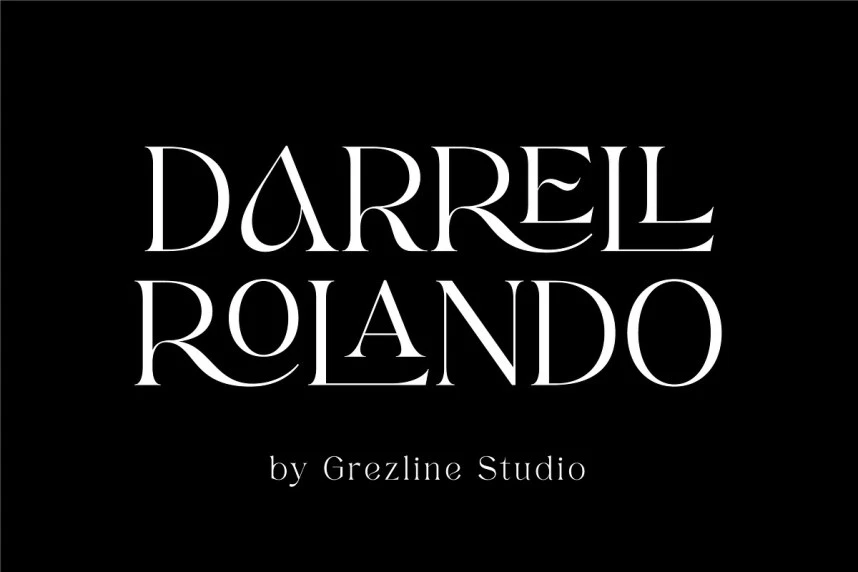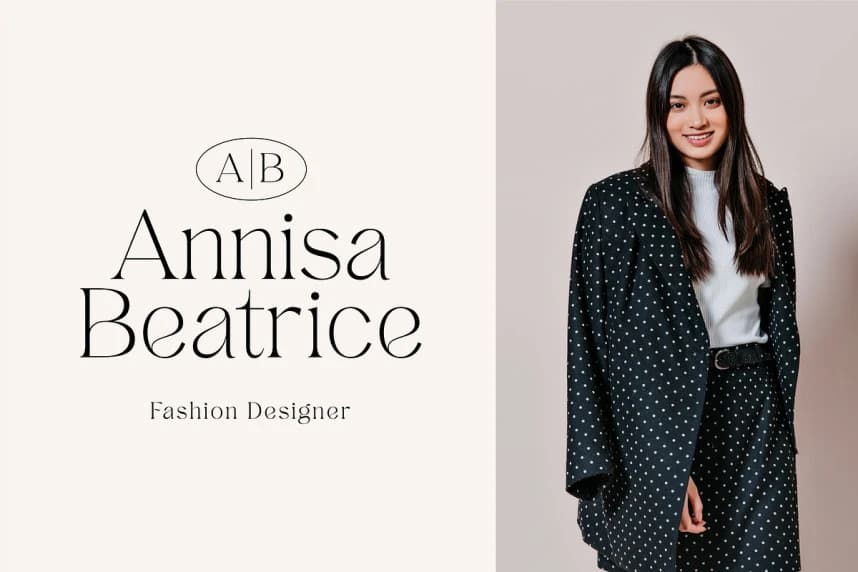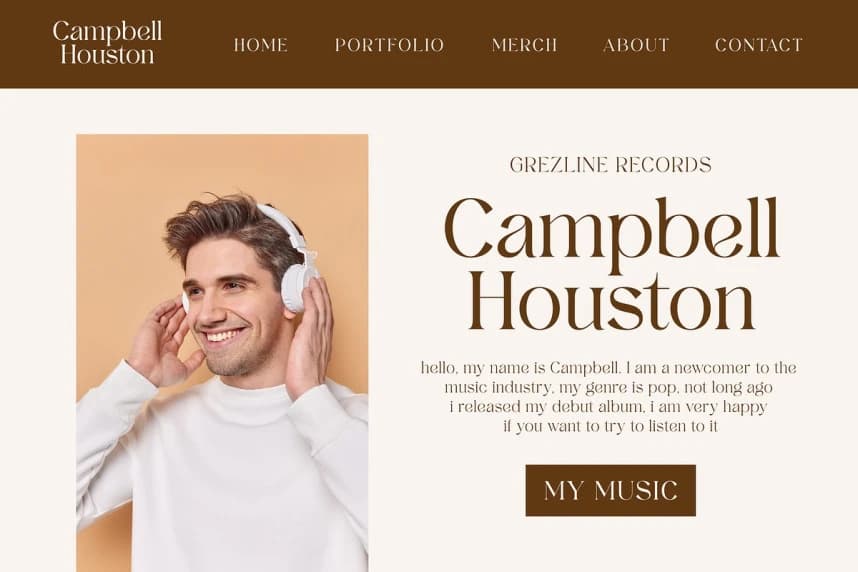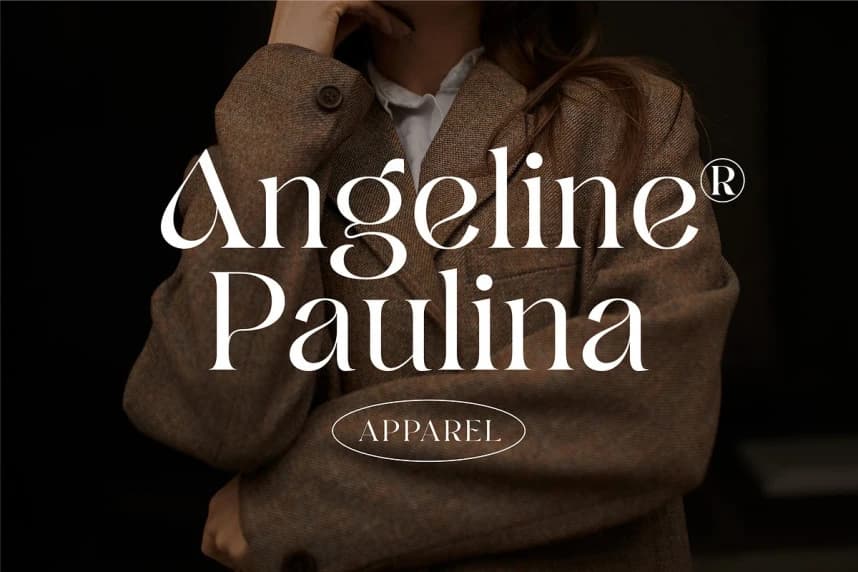
Darrell Rolando Font, vintage ve klasik görünümlere sahip şık bir başlık yazı tipidir. Bu yazı tipi, benzersiz bir ligatür karakter seti ile birlikte gelir. Logo, başlıklar, unvanlar, davetiyeler, etiketler, dergiler, kitaplar, tebrik ve düğün kartları, ambalaj, moda ve makyaj için çok uygundur.
Darrell Rolando Font, vintage ve klasik görünümlere sahip şık bir gösterim yazı tipidir. Bu yazı tipi benzersiz glif ligatürü setine sahiptir. Logo, başlık, unvanlar, davetiyeler, etiketler, dergiler, kitaplar, tebrik/düğün kartları, ambalaj, moda ve makyaj için çok uygundur.